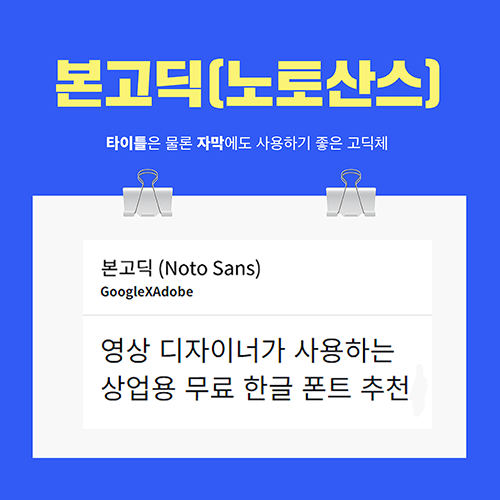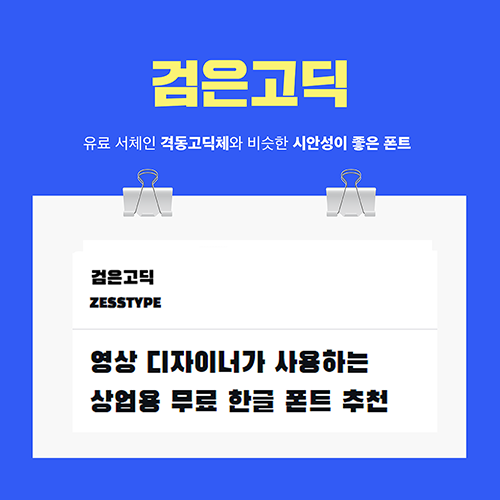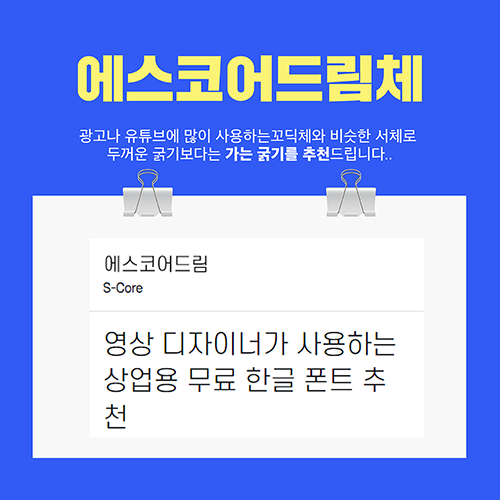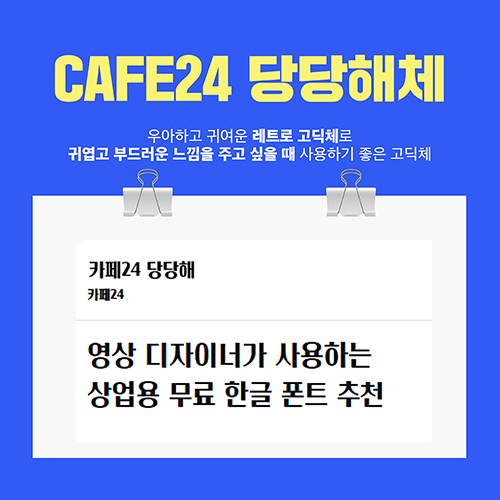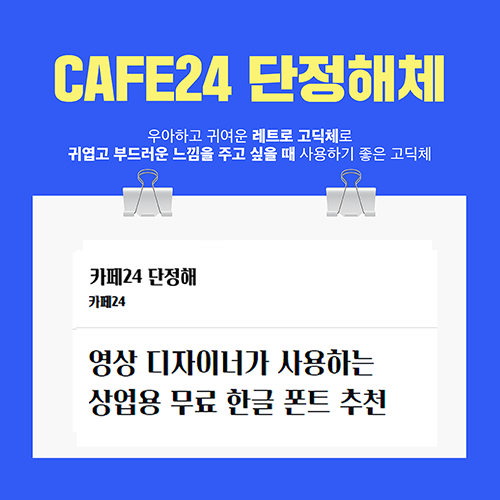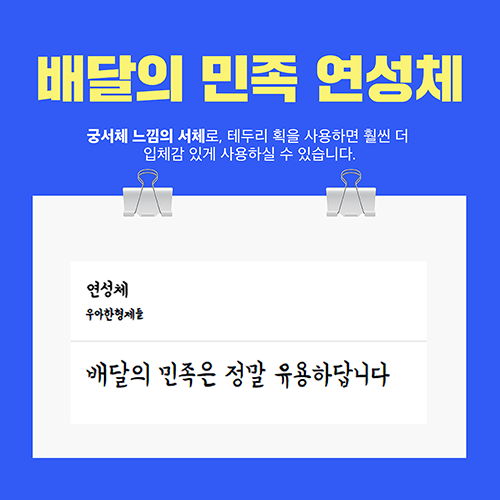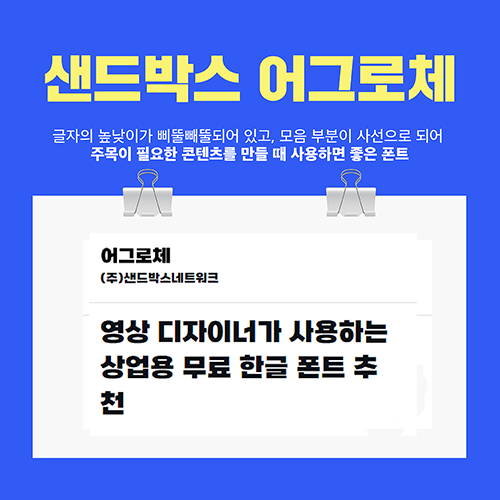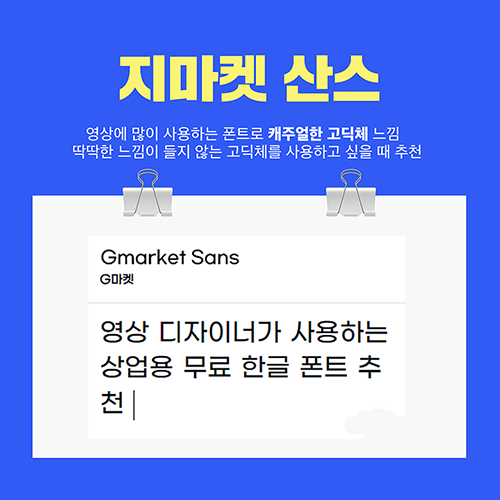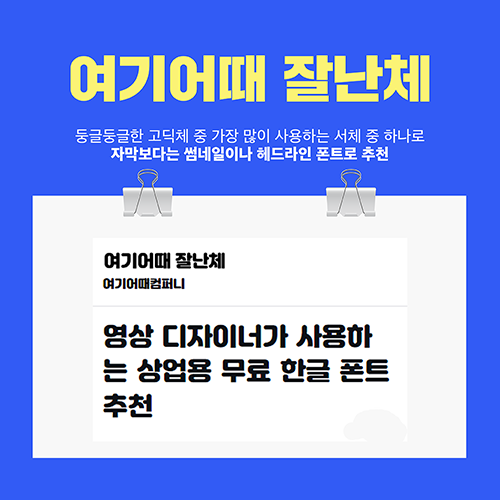
릴스나 숏츠, 유튜브 등 영상 콘텐츠가 대세인 요즘, 영상 편집을 할 때 가장 고민되는 것 중 하나가 바로 영상 폰트 선택인데요. 열심히 편집한 영상이 잘못 선택한 폰트 하나 때문에 망치는 경우가 많습니다. 그만큼 폰트는 영상 편집에 중요한데요. 영상 디자이너가 많이 사용하는 상업용 무료 한글 폰트 추천 드립니다.
1. 노토산스
굵기 종류가 9가지로, 타이틀은 물론 인터뷰 자막에도 사용하면 좋은 노토산스는 영상 제작 초보자들도 사용하면 좋은 믿고 쓰는 고딕체입니다. 글씨 폰트를 어떤걸 사용해야 될지 모르겠을 때, 노토산스나 에스코어드림체를 사용하신다면 적어도 실패할 일은 없습니다. 그만큼 보편적으로 많이 사용하는 폰트이기도 합니다.
2. 검은고딕(블랙한산스)
유료 서체인 산돌폰트의 격동고딕체와 비슷한 느낌을 줄 수 있는 검은고딕체는 시안성이 좋은 폰트로 유튜브 썸네일에 가장 많이 사용하는 서체 중 하나입니다. 숫자나 영문으로 사용해도 예쁜 폰트로 굵기가 두꺼워서 너무 작은 글씨에는 사용하지 않는 게 좋습니다.
3. 에스코어드림체
광고나 유튜브에 많이 사용하는 유료 서체인 꼬딕체와 가장 비슷한 느낌을 줄 수 있는 에스코어드림체는 9개나 되는 두께 옵션으로 노토산스와 함께 가장 많이 사용하는 서체 중 하나입니다. 에스코어드림체는 두꺼운 굵기보다는 가는 굵기가 추천드립니다.
4. cafe2 당당해체, 단정해체
우아하고 귀여운 레트로 고딕체로 추천드리는 카페24 당당해체와 단정해체는 우아하고 부드러운, 그러면서도 귀여운 느낌을 주고 싶을 때 사용하기 좋은 고딕체입니다. cafe24에는 귀여운 폰트들이 많이 있습니다. 귀여운 느낌의 폰트를 찾고 계신 분들이라면 cafe24 폰트 홈페이지에서 더 많은 폰트를 확인해 보세요.
5. 배달의 민족 연성체
배달의 민족 연성체는, 배달의 민족 폰트 3대장(도현체, 한나체, 주아체)과 함께 유튜브나 릴스 등 영상 자막에 많이 사용하는 폰트입니다. 궁서체 느낌의 서체로, 테두리 획을 사용하면 훨씬 더 입체감 있게 사용하실 수 있습니다.
6. 샌드박스 어그로체
글자의 높낮이가 삐뚤빼뚤되어 있고, 모음 부분이 사선으로 되어 있는 것이 특징인 샌드박스 어그로체는 굵기도 3가지로 되어 있어 활용하기 좋은 서체인데요. 굵기가 굵은 서체로, 주목이 필요한 콘텐츠를 만들 때 사용하면 좋은 폰트입니다. 샌드박스 홈페이지에 가면 이 서체와 어울리는 다양한 템프릿도 함께 무료로 다운로드할 수 있어 활용하기 좋습니다.
7. 지마켓산스 폰트
요즘 영상에 많이 사용하고 지마켓체는 캐주얼한 고딕체 느낌의 폰트입니다. 딱딱한 느낌이 들지 않는 고딕체를 사용하고 싶을 때 추천드리는 폰트입니다. 굵기도 3가지로 되어 있어서, 영상 편집에 활용하기 좋습니다.
8. 여기어때 잘난체
둥글둥글한 고딕체 중에서 가장 많이 사용하는 서체 중 하나인 여기어때 잘난체는 자막보다는 썸네일이나 헤드라인 폰트로 추천드립니다. 유튜브에서 많이 사용하는 폰트 중 하나입니다.